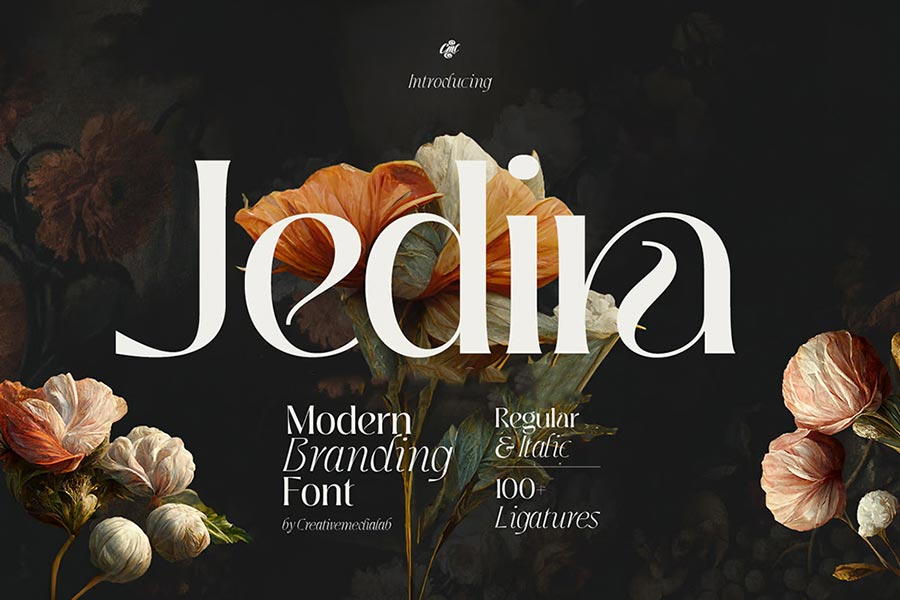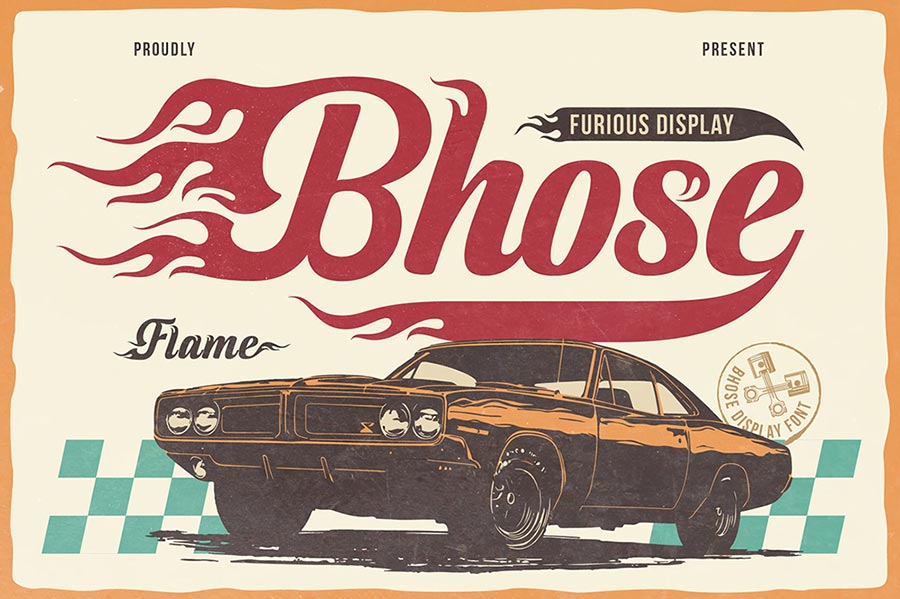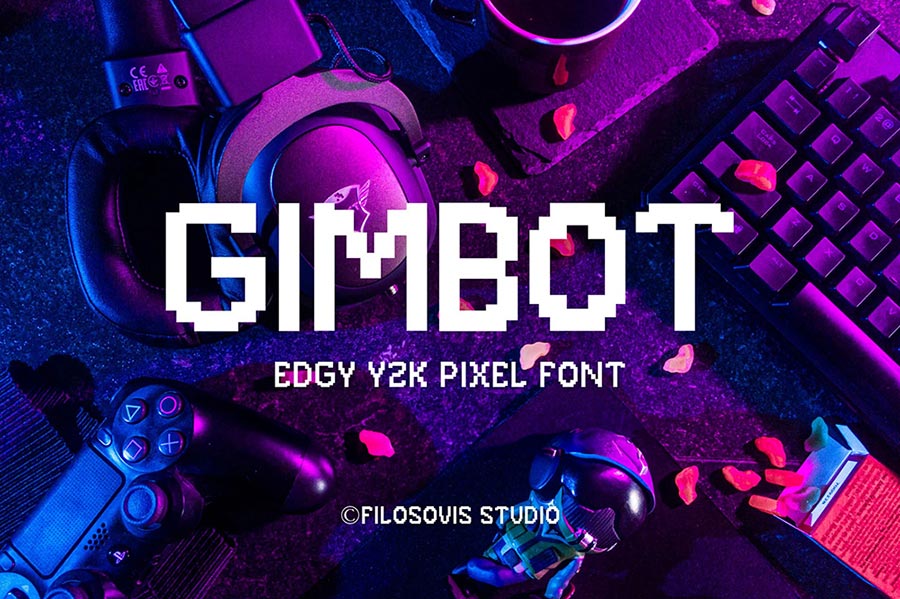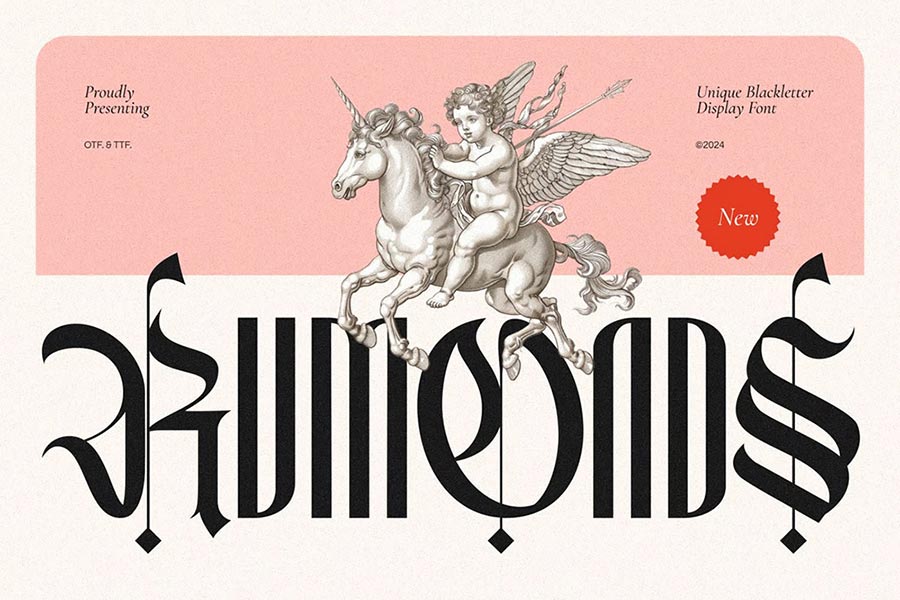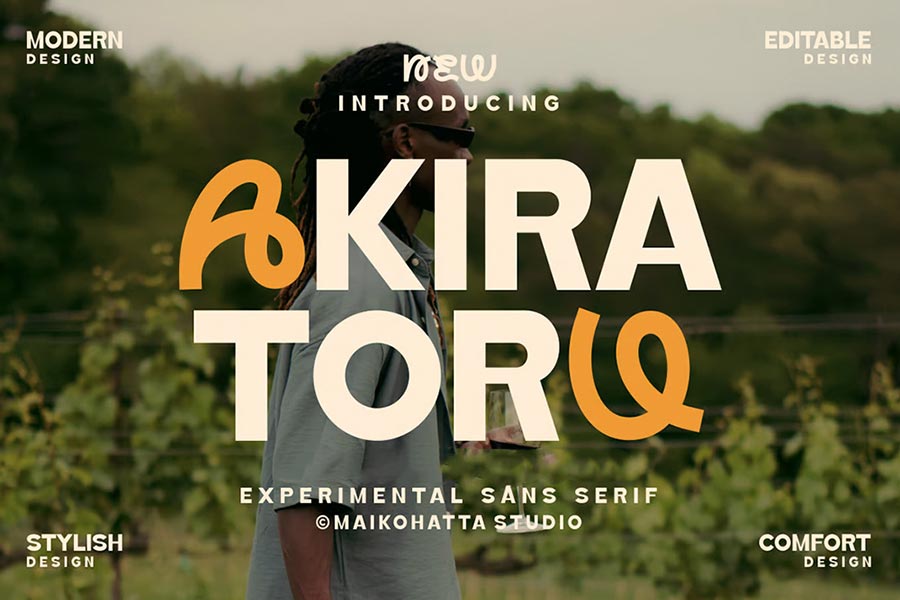
Chia Sẻ Miễn Phí 5 Font Chữ Tuyệt Đẹp Có Chọn Lọc, Mới Nhất Cho Các Dự Án Thiết Kế 2024
Trong thế giới thiết kế đồ họa, việc lựa chọn font chữ phù hợp là một nghệ thuật và cũng là yếu tố quyết định trong việc tạo dựng ấn tượng với người xem. Một font chữ đẹp không chỉ đơn thuần là những ký tự được sắp xếp gọn gàng mà còn là công cụ giúp truyền tải thông điệp một cách mạnh mẽ và rõ ràng. Để giúp bạn tìm được những lựa chọn phù hợp cho các dự án thiết kế, dưới đây là một số gợi ý font chữ đẹp với những phong cách đa dạng, có thể sử dụng trong nhiều loại hình thiết kế khác nhau.
Font chữ không chỉ là công cụ truyền đạt thông tin, mà nó còn là yếu tố quyết định trong việc tạo dựng ấn tượng và nâng cao giá trị thẩm mỹ của mỗi thiết kế. Một font chữ đẹp không chỉ mang lại sự dễ đọc mà còn có khả năng thể hiện cá tính, phong cách của thương hiệu hoặc thông điệp mà bạn muốn truyền tải. Dưới đây là một số ưu điểm của font chữ đẹp trong thiết kế:
1. Tăng Cường Trải Nghiệm Người Dùng
Font chữ đẹp giúp người đọc cảm thấy dễ dàng và thoải mái hơn khi tiếp nhận thông tin. Một font chữ dễ đọc, rõ ràng sẽ giúp người dùng hiểu nhanh chóng nội dung mà không gặp phải sự khó chịu. Trong thiết kế web hoặc ứng dụng, việc chọn font chữ phù hợp giúp tăng cường trải nghiệm người dùng (UX), làm cho các trang web hoặc ứng dụng trở nên dễ sử dụng và tiếp cận hơn. Điều này đặc biệt quan trọng đối với những trang web có lượng văn bản lớn, như blog hoặc các bài viết dài.
2. Tạo Dấu Ấn Thương Hiệu
Một font chữ đẹp, độc đáo và dễ nhận diện giúp tạo nên dấu ấn mạnh mẽ cho thương hiệu. Những thương hiệu nổi tiếng như Coca-Cola, Google, hay Disney đều có những font chữ đặc trưng riêng, giúp người tiêu dùng dễ dàng nhận diện và nhớ lâu. Việc sử dụng font chữ đẹp và phù hợp với giá trị thương hiệu giúp nâng cao tính nhất quán trong các chiến dịch marketing, quảng cáo và tạo sự liên kết cảm xúc với khách hàng.
3. Thể Hiện Phong Cách và Cá Tính
Mỗi loại font chữ mang một phong cách và cá tính riêng biệt. Font chữ serif (có chân) thể hiện sự lịch lãm và trang trọng, trong khi font chữ sans-serif (không có chân) lại mang đến cảm giác hiện đại, năng động. Font script (chữ viết tay) mang lại sự ấm áp, gần gũi, và lãng mạn. Nhờ vào sự đa dạng này, bạn có thể dễ dàng lựa chọn font chữ để thể hiện phong cách thiết kế của mình, từ các dự án cá nhân hóa cho đến những chiến lược thương hiệu lớn.